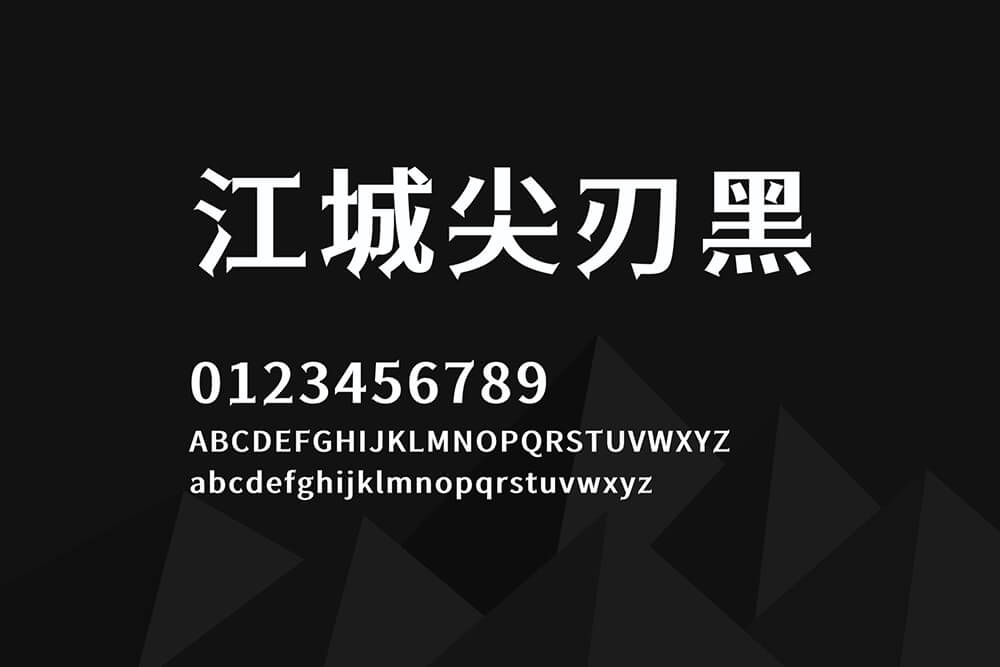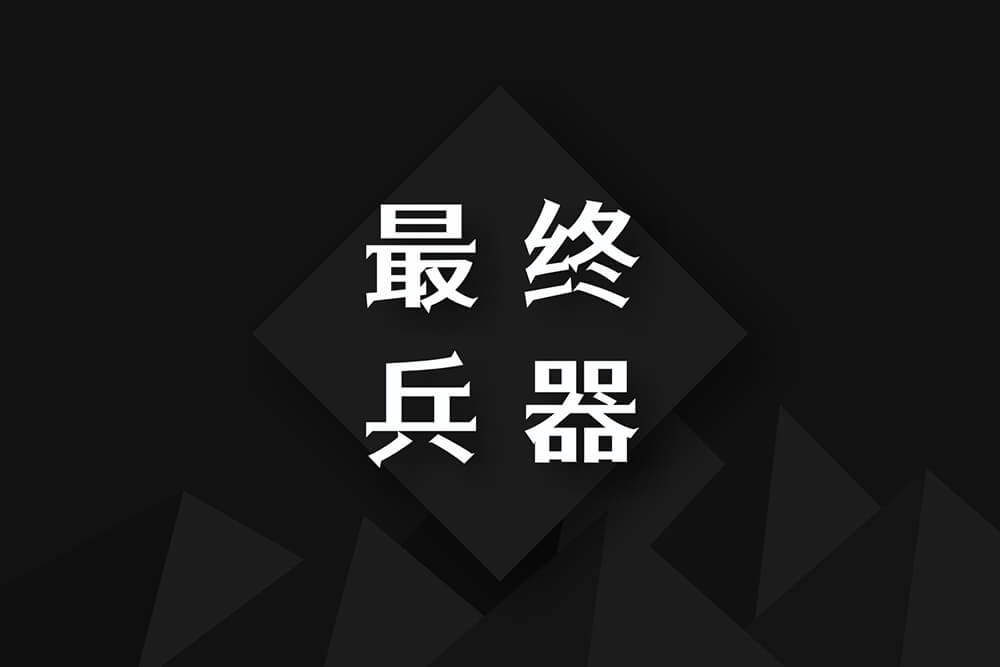
江城尖刃黑是作者刘鹏(微博 @设裂星辰)基于思源黑体,并在狮尾福腿黑体 SC 的基础上改造而成的一款免费商用中文字体。
作者在狮尾福腿黑体的基础上,放大了笔画末端的三角形突刺,尤其是撇和捺的收笔处特意减少了粗度,使尖角更加突出,让整个字形看起来像“利刃”一样,极具攻击性和辨识度。同时,拉大了横细竖粗的比例差,形成粗细不一、纵横交错的视觉效果。特别适合海报主标题、游戏 UI、潮牌 Logo、短视频封面等需要强视觉冲击力的场景。